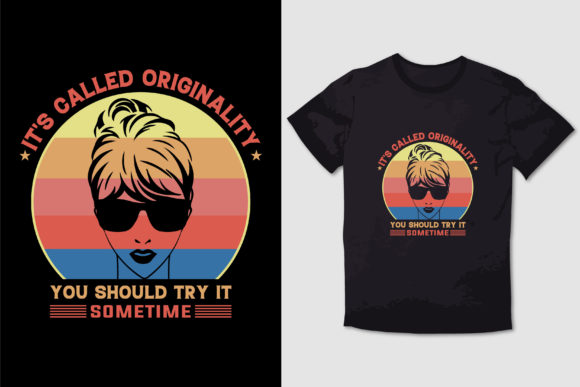
IT'S CALLED ORIGINALITY YOU SHOULD TRY I
IT'S CALLED ORIGINALITY YOU SHOULD TRY IT – Avaliação Completa
Se você está em busca de um design tipográfico que combine estilo retro, criatividade e alta qualidade, o arquivo “IT'S CALLED ORIGINALITY YOU SHOULD TRY IT” é a escolha perfeita. Disponível em SVG, PNG, AI e EPS, ele atende às necessidades de designers, empreendedores de Print‑On‑Demand e amantes de moda que querem se destacar.
- Versatilidade incomparável – O design funciona em camisetas, quadros, cartões de aniversário, adesivos vinílicos, transferências a ferro, gravuras e até scrapbooking.
- Design vintage e tipográfico – A frase impactante “IT'S CALLED ORIGINALITY YOU SHOULD TRY IT” traz um toque retro que agrada tanto ao público jovem quanto ao adulto.